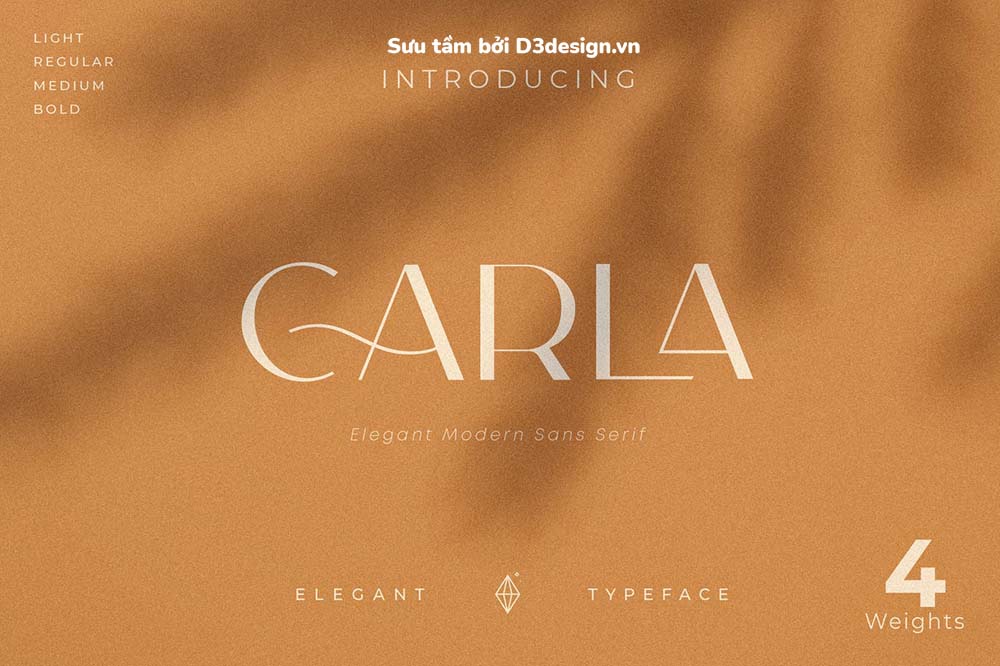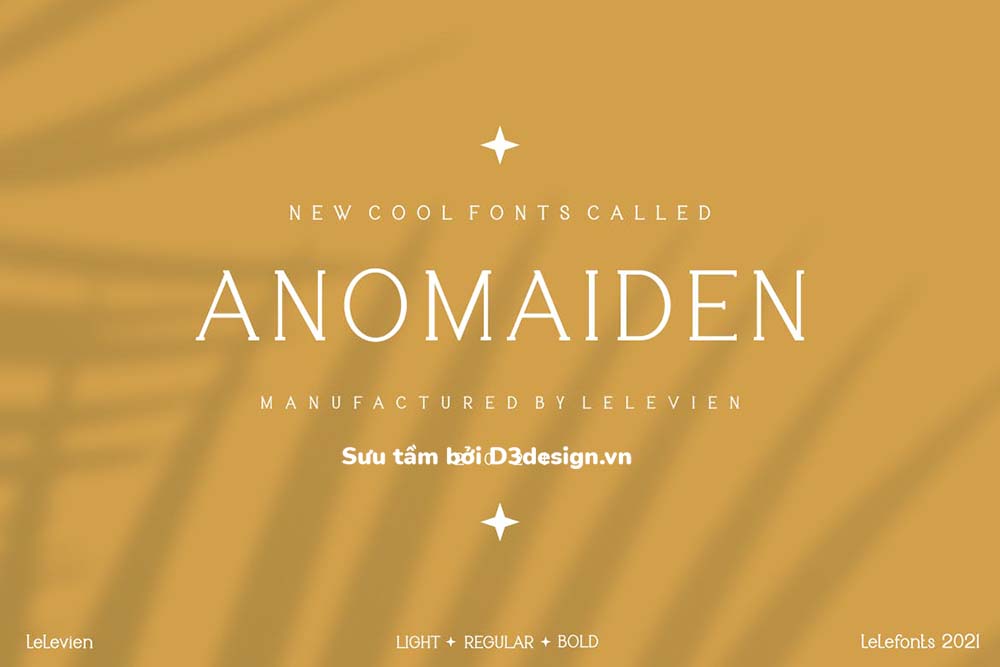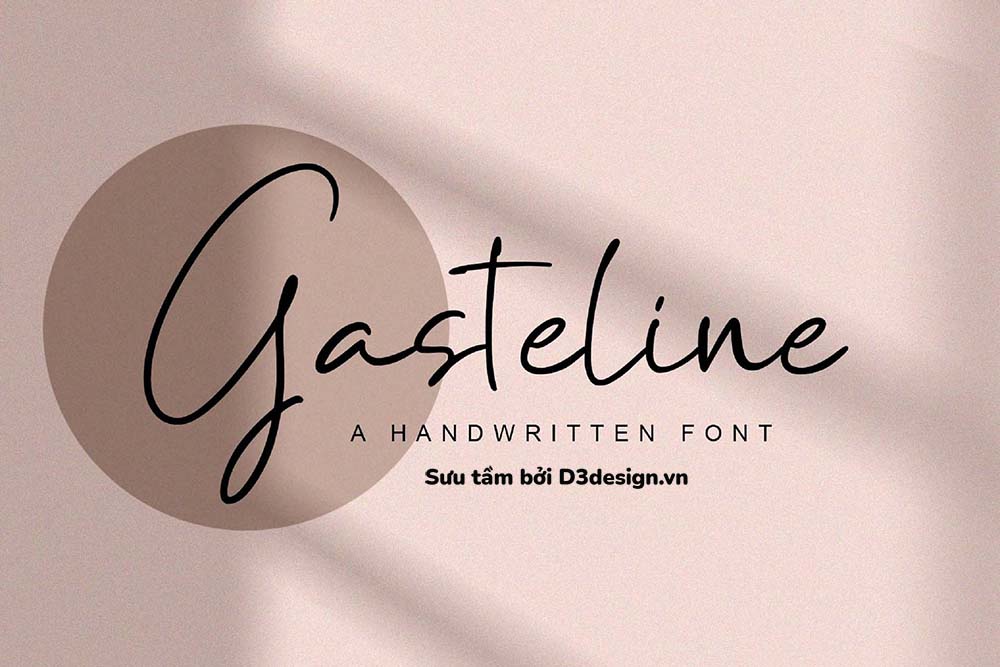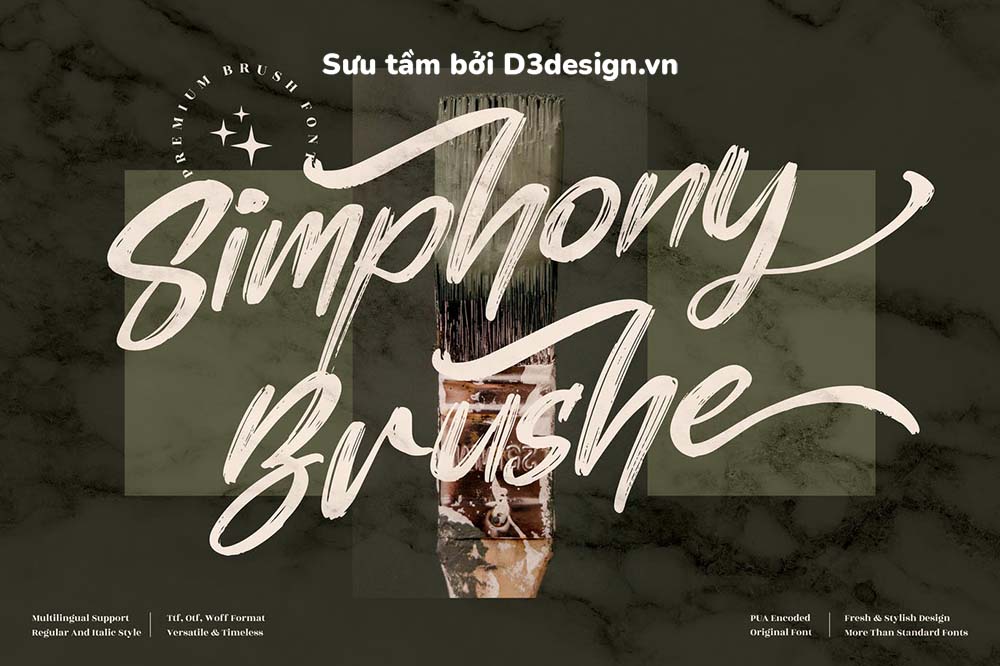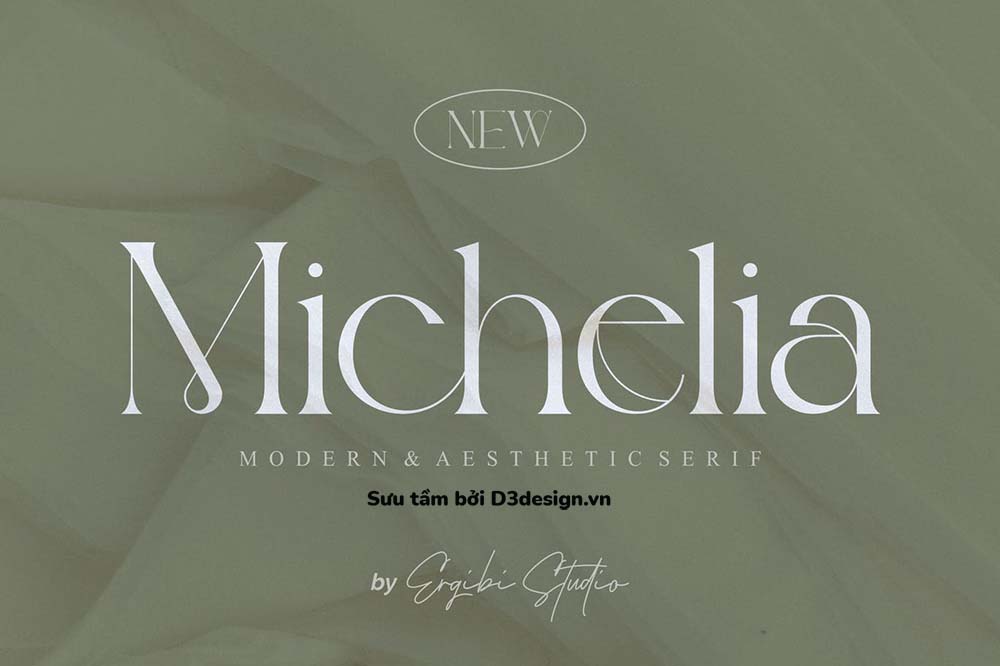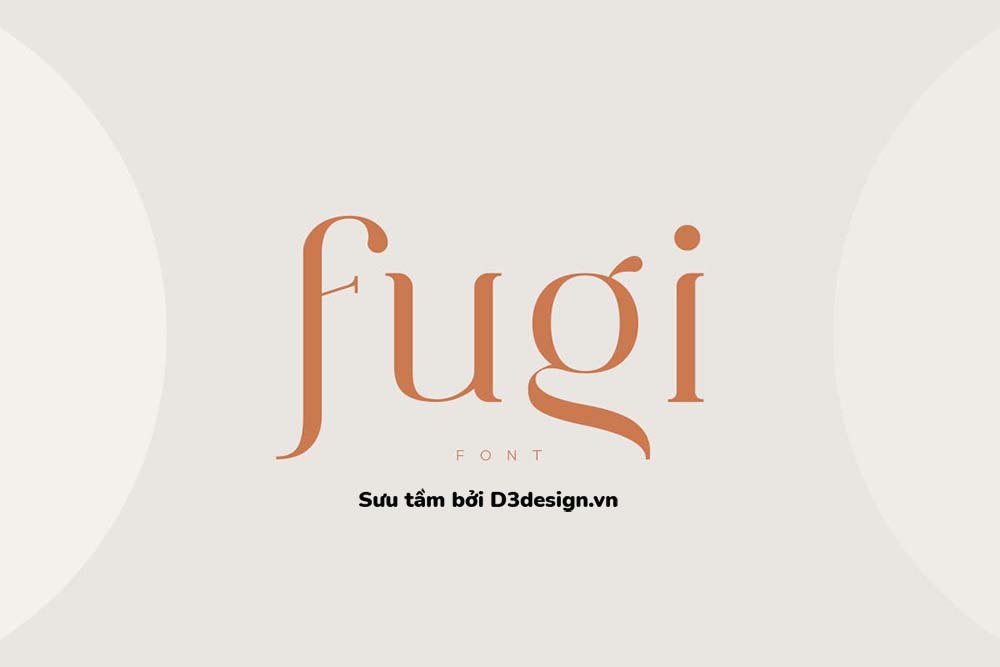
Tải Font Chữ Thanh Mảnh Cực "Đẹp" Và Hoàn Toàn Miễn Phí 2022
Có rất nhiều phông chữ đa dạng và sáng tạo dành riêng cho bạn. Nhưng chúng tôi đã chọn lọc ra những viên “kim cương” quý giá nhất trong hàng ngàn phông chữ. Vì thế, 6 font chữ thanh mảnh và sang trọng mà D3design chia sẻ dưới đây chính là vũ khí quan trọng để nâng tầm thiết kế của bạn.